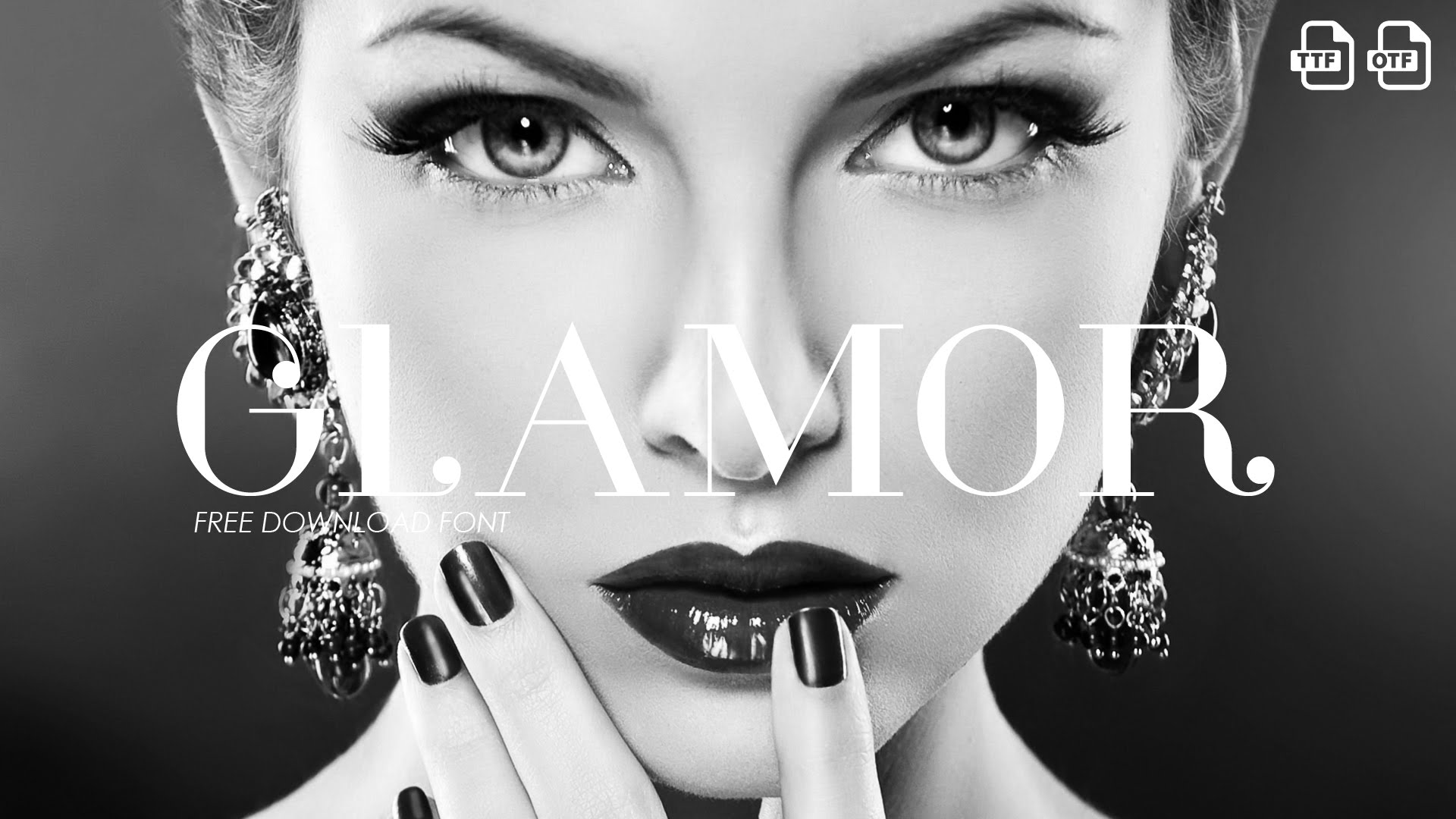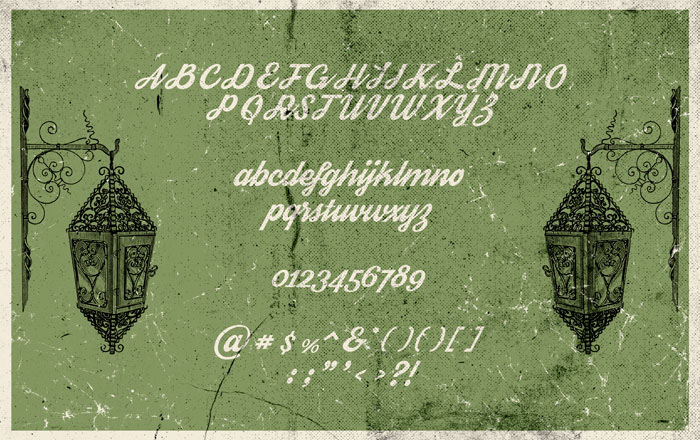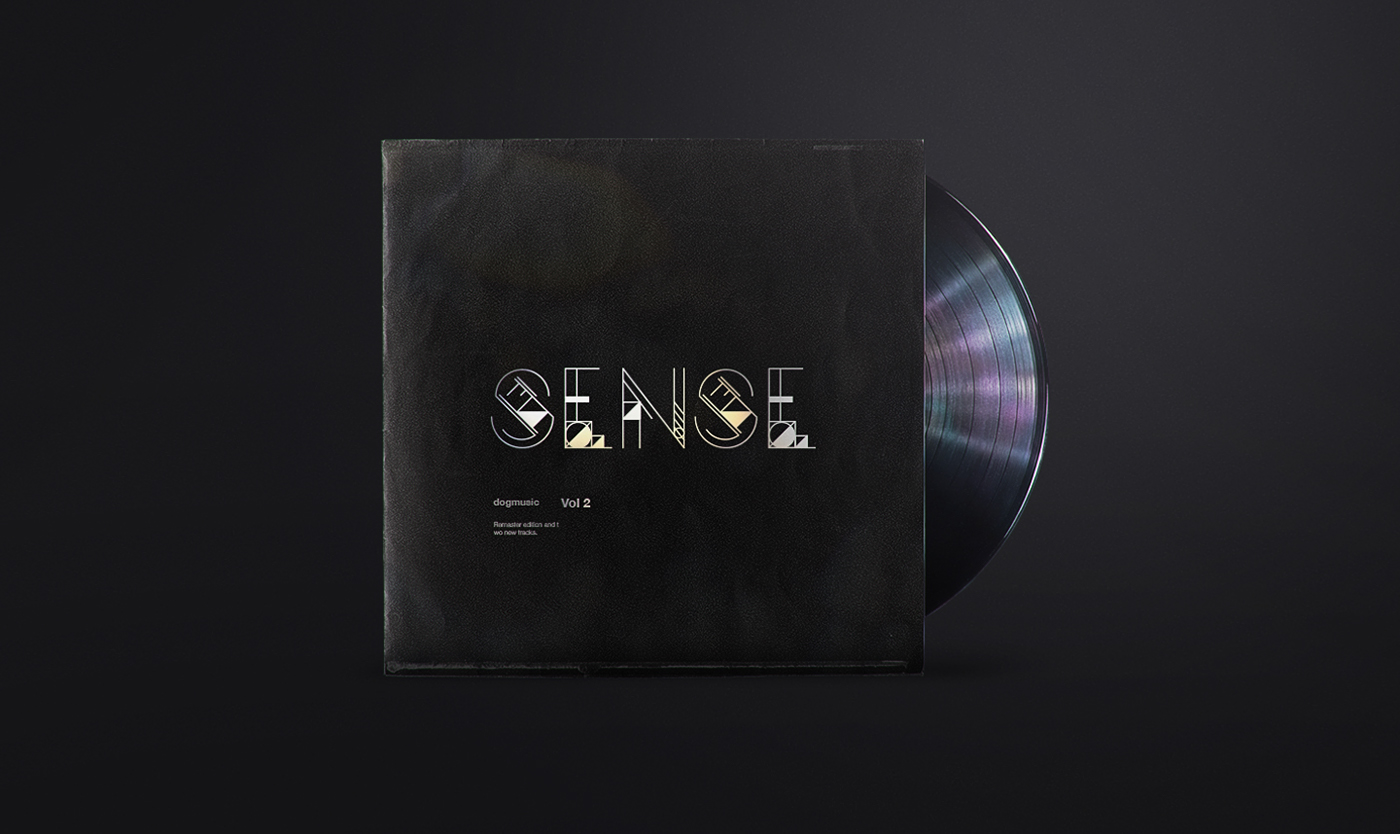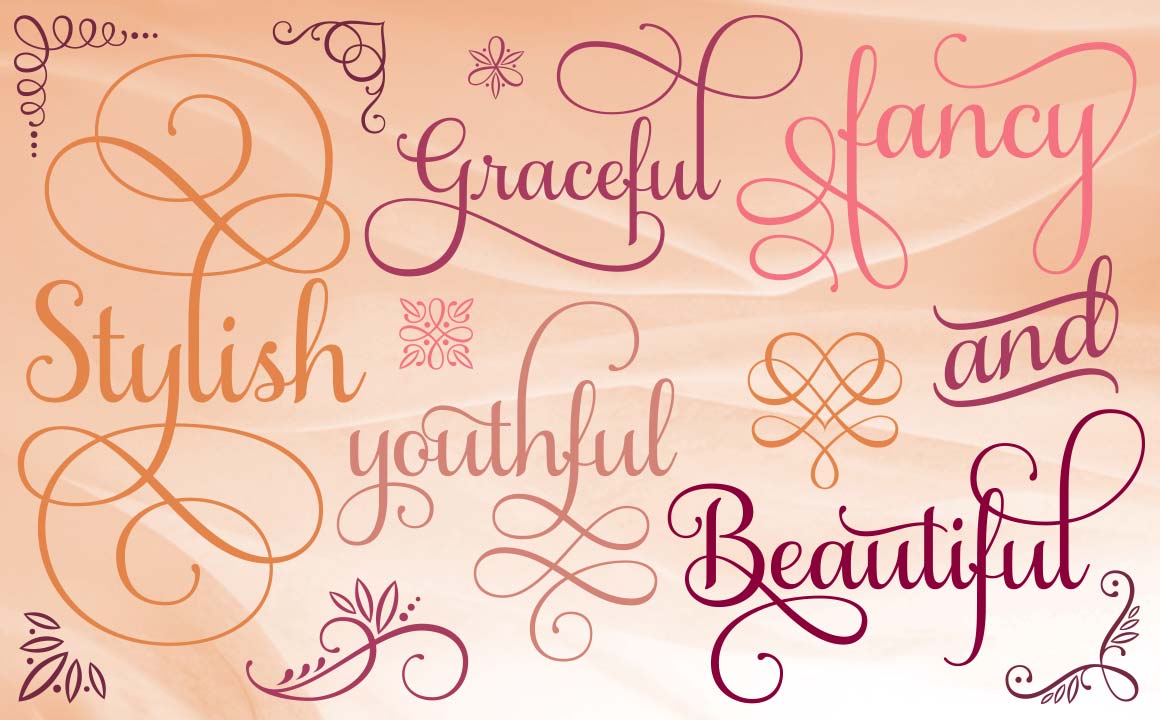
1. Elegant Gentleman
Nghe tên đã thấy "chanh sả" rồi đúng không nè! Gentleman mang vibe lịch lãm, gọn gàng và tinh tế y như các anh quý ông khoác vest sang chảnh vậy. Font này "cân" mọi thiết kế logo hay poster cao cấp luôn. Xài làm tiêu đề hay bài viết cũng "ngon" lắm đó!
2. Glamor
Đây là "bé cưng" của giới thời trang luôn nha! Với tận 24 kiểu chữ khác nhau, sang xịn mịn và cực kỳ hiện đại. Nhìn đâu cũng thấy Glamor - từ poster, bìa sách cho đến tạp chí và website thời trang...
Muốn thiết kế tên thương hiệu riêng, dễ nhớ dễ "flex" thì chọn Glamor là xong xuôi, để "em ấy" lo hết à!
3. GEOM
Lấy cảm hứng từ hình học và nét kẻ đơn giản, GEOM mang vibe thoải mái và phóng khoáng cực chill
Đây là "đứa con tinh thần" của giám đốc nghệ thuật Danilo Gusmão Silveira từ São Paulo, được hội designer mê tít luôn! Xài font này cho bìa album, tạp chí hay poster phim là có ngay sản phẩm sáng tạo và thẩm mỹ "xịn xò" lắm nha!
4. Samantha Script
Bộ font có style nhẹ nhàng, thanh thoát đi kèm tận 1.100 ký tự thay thế với độ phức tạp khác nhau luôn nè!
Samantha Script cho phép bạn tùy chỉnh phông chữ theo ý muốn để tạo hiệu ứng "perfect" nhất. Muốn làm quote "sâu sắc" thì chọn font này là "chuẩn bài" rồi!
5. Futuracha
Được mệnh danh là font tự tiến hóa, Futuracha từng gây "bão" khắp các diễn đàn thiết kế luôn á!
Mà cái tên cũng "cute" phết: ghép từ "future" và "cucaracha" (tiếng Tây Ban Nha nghĩa là con gián đó). Độc đáo chưa nào!
6. Streetwear
Muốn có font chữ mang hơi hướng vintage cổ điển pha chút "chất đường phố" thì Streetwear chính là "chân ái" của bạn đây!
Lấy cảm hứng từ thập niên 60-70, bạn sẽ bắt gặp nó ở khắp nơi: từ áo phông, túi hàng hiệu cho đến logo và poster đường phố luôn!
7. Carioca
Khác hẳn với các font khác, Carioca là font cực kỳ vui tươi do 2 nhà thiết kế Tano Veron và Yai Salinas tạo ra nè!
Với màu sắc thay đổi trong từng chữ cái, Carioca sẽ là "must-have item" khi bạn làm poster hay bìa album cần độ sáng tạo "bùng nổ" đó!
8. Bauru
Lấy cảm hứng từ Jazz và Soul, Bauru là tâm huyết của designer Pier Paolo. Đây chắc chắn sẽ là font đầu tiên bạn nghĩ tới khi thiết kế cho quán cafe, phòng trà hay các thương hiệu về âm nhạc luôn!